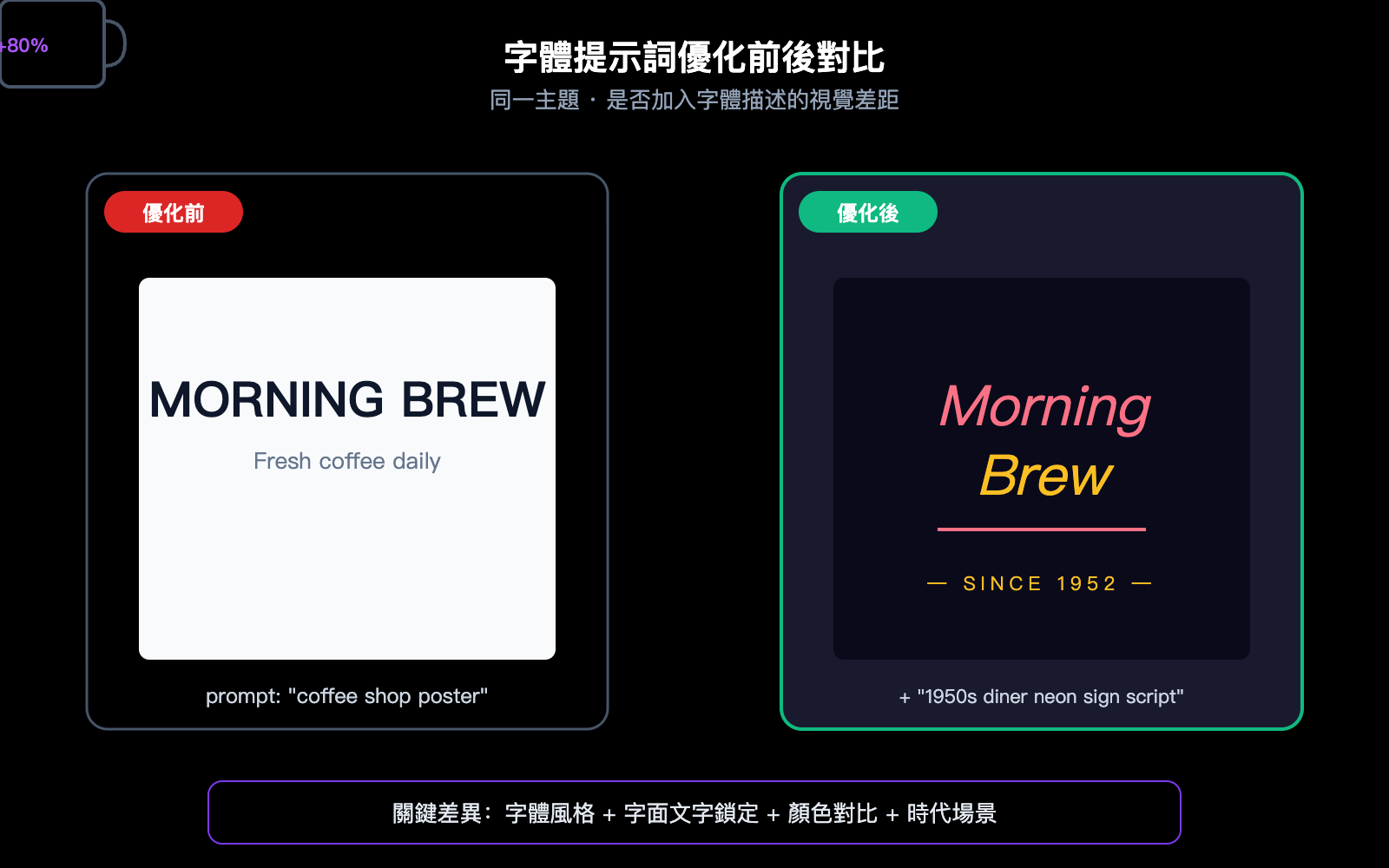
gpt-image-2 API 字體提示詞完全指南:6 種描述法讓出圖美感提升 80%
很多用戶在使用 gpt-image-2 API 或 ChatGPT 官網出圖時都會遇到同一個問題:模型生成的圖片雖然文字識別度很高,但字體永遠是那種"工程師審美"的樸素無襯線體,缺少品牌感與設計感。這種"樸素美學"在生成海報、社媒封面、產品宣傳圖時尤其明顯,讓本來不錯的構圖也顯得廉價。
問題的根源不在於模型能力不足,而在於絕大多數用戶的提示詞裏只描述了"畫什麼",卻沒告訴模型"字體應該長什麼樣"。本文基於 OpenAI 官方 Cookbook 與多家 API 服務商的實測經驗,系統拆解 gpt-image-2 字體提示詞的工作機制,給出 6 套可直接複用的字體描述模板,並結合 API易 apiyi.com 平臺的調用示例,幫你在 5 分鐘內學會讓出圖字體真正"有美感"的提示詞寫法。
一、gpt-image-2 字體提示詞的核心機制
1.1 爲什麼默認出圖字體總是樸素無襯線
gpt-image-2 在沒有明確字體描述時,會根據訓練數據中"最安全"的視覺先驗生成字體,結果往往是中性的幾何無襯線體(接近 Inter、Helvetica 風格),保證識別率但犧牲了風格化表達。
OpenAI 官方提示詞指南明確指出:模型只會渲染你主動約束的視覺屬性,沒有約束的部分一律走默認值。也就是說,如果你只寫"a poster about coffee",模型會自動選用最普通的字體;只有當你寫出"hand-lettered display serif with thick brushstrokes"這種細節,模型纔會觸發對應的字體先驗。
這就是爲什麼同一張主題、同一個 prompt 長度,加了字體描述與沒加字體描述的成片質量可以差出一個等級。理解這一點之後,"出圖字體樸素"就不再是模型缺陷,而是用戶沒有把字體當成圖像的核心信息去描述。
另一個常被忽略的因素是模型版本。gpt-image-2 相比 1.5 代最大的升級就在文字渲染層,原生支持近 4K 輸出,對小字、密集排版、多字體混排的處理能力都顯著提升,這也意味着在 gpt-image-2 上花在字體提示詞上的精力回報率更高,值得投入更多時間打磨。
1.2 gpt-image-2 字體提示詞的四大核心要素
把"字體描述"這件事拆開看,gpt-image-2 實際上是在響應四個獨立維度的指令,缺一不可:
要素 作用 示例描述
字體風格 (Style) 決定字形結構與視覺性格 bold sans-serif、condensed serif、hand-lettered display
字號層級 (Hierarchy) 控制標題/副標題/正文的對比 large headline, small body copy
顏色對比 (Contrast) 決定字體與背景的可讀性 high contrast white on navy
空間佈局 (Placement) 鎖定文字位置與對齊方式 centered at top, clean kerning
1.3 字面文字的強約束寫法
OpenAI Cookbook 的 image-gen-models-prompting-guide 給出一條關鍵技巧:把要出現在畫面裏的字符串用引號或全大寫包裹起來,模型會把這部分理解爲"必須按字面渲染、不能多字也不能錯字"的硬約束。
實測對比下來,寫 the word coffee on a sign 和寫 a sign with the EXACT text "COFFEE" 出現拼寫錯誤的概率差異顯著,後者幾乎能保證字符級一致。難拼的品牌名(例如 Schønne、APIYI)建議用空格隔開逐字符拼寫,例如 "A P I Y I",進一步降低字符錯位風險。
二、gpt-image-2 字體提示詞的 6 種實戰描述法
不同場景適合不同的字體描述策略。以下 6 種方法是從 OpenAI 官方示例、fal.ai 實測案例與開源 prompt 庫中歸納出來的高頻可複用模板。
2.1 功能描述法:最穩的基礎寫法
直接用排印學術語描述字形特徵,這是 OpenAI 官方最推薦的寫法,命中率最高:
• bold geometric sans-serif(厚重幾何無襯線,適合科技品牌)
• condensed sans-serif with tight tracking(緊湊窄體,適合雜誌標題)
• classic transitional serif with fine hairlines(精細襯線體,適合奢侈品/出版物)
• rounded humanist sans-serif(圓潤人文無襯線,適合兒童/友好品牌)
2.2 風格情緒法:讓字體有"性格"
用藝術運動或設計風格替代具體字體名,觸發模型對整套美學體系的先驗:
• minimalist Bauhaus sans-serif
• Art Deco display typography with metallic strokes
• brutalist concrete typography
• Memphis-style 80s display font with bold geometric shapes
這種寫法的好處是字體不會孤立存在,模型會自動匹配相符的顏色、版式、裝飾元素,整張圖的設計語言會更統一。
2.3 時代場景法:精準復刻懷舊美學
通過年代+載體的組合,讓字體看起來像是從特定歷史時期的真實印刷品上掃描下來:
• 1970s vinyl record cover psychedelic display font
• 90s grunge zine handwritten typography with photocopy texture
• early 2000s Y2K chrome bubble font
• 1950s diner neon sign script lettering
時代場景法對生成懷舊、復古、地下文化主題的封面尤其好用,比單純寫 retro font 精準度高出一個數量級。
2.4 品牌氛圍法:商業級出圖首選
直接描述目標行業的視覺氣質,讓模型自動靠近成熟的商業字體規範:
• editorial fashion magazine serif typography, Vogue style
• tech startup landing page typography, clean and confident
• luxury skincare branding typography, refined and minimal
• craft brewery label typography, hand-drawn rustic feel
2.5 物理材質法:讓字體"立體存在"
把字體視爲現實世界中的物理對象,而非純數字圖層。這是 fal.ai 教程裏強調的高級用法:
• plastic letter board with uneven letter spacing, one missing slot
• glowing neon tube letters with visible glass tubing and cables
• cut paper letters with soft drop shadows, layered cardboard
• chiseled marble inscription with deep shadow inside the cuts
物理材質法生成的字體會自帶光照、陰影、磨損細節,質感遠超平面貼字。
2.6 參考字體名法:精準復刻特定字型
雖然 OpenAI 官方沒有公開支持的字體白名單,但實測主流知名字體名是可以被識別的,作爲輔助修飾詞加在功能描述後效果最好:
• clean sans-serif typography, Inter style
• editorial serif similar to Playfair Display
• geometric sans-serif inspired by Futura
• humanist serif in the vein of Garamond
注意這種寫法是風格暗示而非字符級復刻,模型不會真的調用字體文件,但視覺感覺會非常接近。
描述法 適用場景 命中率 風格豐富度
功能描述法 通用、UI、企業 ⭐⭐⭐⭐⭐ ⭐⭐⭐
風格情緒法 海報、藝術、個性品牌 ⭐⭐⭐⭐ ⭐⭐⭐⭐⭐
時代場景法 復古、懷舊、文化主題 ⭐⭐⭐⭐ ⭐⭐⭐⭐⭐
品牌氛圍法 商業、電商、廣告 ⭐⭐⭐⭐ ⭐⭐⭐⭐
物理材質法 立體場景、產品攝影感 ⭐⭐⭐ ⭐⭐⭐⭐⭐
參考字體名法 精準復刻、設計師場景 ⭐⭐⭐ ⭐⭐⭐⭐
三、gpt-image-2 字體提示詞的 API 實戰調用
理解了描述方法之後,下一步是怎麼把這套提示詞傳給 gpt-image-2 API。這一節給出最簡調用代碼與關鍵參數說明。
3.1 極簡調用示例:讓字體提示詞生效
下面這段 Python 代碼使用 OpenAI SDK 調用 gpt-image-2,字體提示詞放在 prompt 主體裏即可生效:
注意 prompt 裏同時包含了"畫什麼 + 字面文字 + 字體描述 + 顏色對比 + 位置"五個維度,這是高質量出圖的最小完備結構。
3.2 關鍵參數:quality 對字體清晰度的影響
gpt-image-2 的 quality 參數對小字、密集排版、多字體混排的影響遠大於對畫面整體觀感的影響:
六、總結:讓 gpt-image-2 字體真正有美感的關鍵路徑
回到開頭的問題——爲什麼 gpt-image-2 出圖字體總是樸素無美感?答案是:模型只渲染你主動約束的屬性。一條專業級字體提示詞必須同時覆蓋字體風格、字號層級、顏色對比、空間佈局四要素,再疊加引號鎖定字面文字、quality 參數設爲 high、必要時配合參考圖。
本文給出的 6 種描述法(功能描述、風格情緒、時代場景、品牌氛圍、物理材質、參考字體名)覆蓋了絕大多數商業出圖場景。建議先從功能描述法上手,逐步疊加風格情緒與品牌氛圍,最後用結構化字體規範段固化下來作爲團隊複用模板。
字體不是圖像的裝飾,而是圖像的靈魂。掌握 gpt-image-2 字體提示詞的寫法,本質上是把"提示詞工程"從畫面構圖層面延伸到排印設計層面,這也是 AI 圖像生成從"能看"走向"專業級"的關鍵一躍。